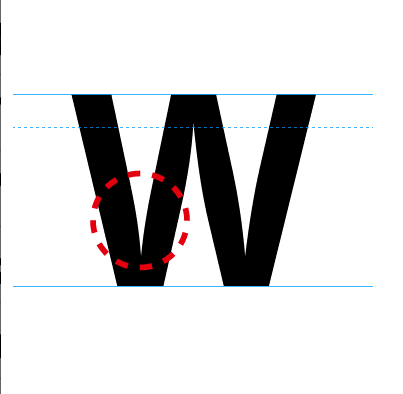
Strichstärkenverjüngung bei klassischen Schriften
Hallo, hab letztens mit unserem Siebdrucker diskutiert und wir sind beide nicht auf den Fachbegriff gekommen wie man die Verjüngung nennt die man bei klassischen Schriftschnitten oft sieht »siehe Anhang«. Wir waren beide der Meinung das dies dem Zulaufen bei kleinen Schriftgrößen entgegenwirkt. Aber wie heisst das genau ...